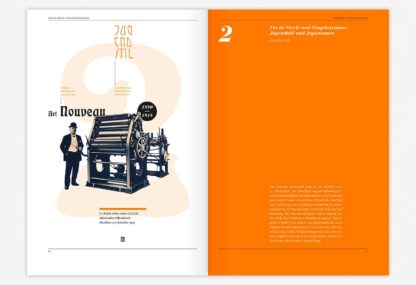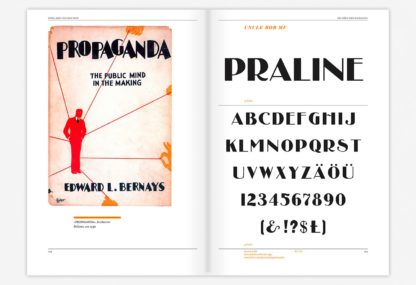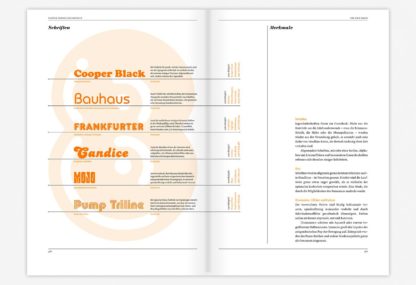
Zeitgeist aus der Flasche befreit – eine typografische Reise zurück in die Zukunft.
Schriften sind Kinder ihrer Zeit. Implizit tragen sie den Geist der Epoche in sich, in der sie entstanden sind. Deren kulturelle und politische, soziale und ästhetische Normen und Werte. Sie sind also immer auch Zeitgeistschriften. Natürlich ist Gestaltung immer Zeitzeugnis: im Gegensatz zu Kunst und Design aber fliegt das Typedesign unter dem Radar intellektueller Dekodierung durch breitere gesellschaftliche Schichten.
Das macht es umso reizvoller, the power of type heute gestalterisch einzusetzen, um Assoziationen zu historischen Epochen, Werten und Haltungen zu wecken. Weil »normale« Menschen Buchstaben als Mikropartikel der visuellen Kommunikation zwar lesen, nicht aber bewusst wahrnehmen, kann man mit Schriftwahl und -einsatz ähnlich unterbewusst kommunizieren wie mit Duft oder Sound. Die gute alte Zeit heraufbeschwören oder an die Stilsicherheit der Klassischen Moderne appellieren. Das macht Retrofonts zu einem Werkzeugkasten der Superlative.
Was bietet dieses Buch?
Gregor Stawinski trägt über 400 starke Schriften aus den Stilepochen vom Historismus bis in die Roaring Eighties zusammen, sortiert sie den Epochen zu, zeigt deren Wirkung in Figurenverzeichnissen und stellt aktuelle und historische Anwendungsbeispiele vor. So sensibilisiert er für die Schriften und ihren Einsatz in der Gestaltung und weckt die Lust darauf, aktueller Gestaltung mehr oder weniger stark historischen Kontext einzuhauchen.
Von typografischen Verkleidungs-Kunststücken bis zum subtilen Hauch der Historie ist alles möglich. Das entscheidet die Aufgabe.
Was sind die klassischen Einsatzgebiete für Retrotype?
Im Gegensatz zu uns Menschen machen sich Marken und Produkte, Cafés und Kneipen gerne etwas älter als sie sind. Die Glattheit der digitalen Welt steigert die Sehnsucht nach einer Zeit, in der das Handwerk den Takt vorgab, in der handmade alternativlos war. Dementsprechend nutzen Micro-Breweries, Independent-Labels, Startups der Maker-Szene the power of type, um sich visuell eine Geschichte zu geben, die sie so noch gar nicht haben.
Auch Packaging und Interieur Design spielen gern mit typografischen Zeitreisen. In der Buchgestaltung und im Bereich der Kulturplakate wird die Zeitgeist-Codierung gern etwas subtiler eingesetzt.
Ihrer Fantasie sind keine Grenzen gesetzt, das Spiel kann aber vor Profiaugen nach hinten losgehen, wenn Sie knapp daneben landen. Deshalb sind neben den Schriften die Anwendungsbeispiele – und die Auseinandersetzung mit ihnen – so wichtig.
Zu Ausstattung und Gestaltung
Retrofonts
Über 400 der beliebtesten Retrofonts aus zwei Jahrhunderten Typedesign
Ob eine Schrift Retro ist, entscheidet erst der Kontext, in dem sie eingesetzt wird, und so wie bei der Mode dreht sich auch hier alles um Look and Feel.